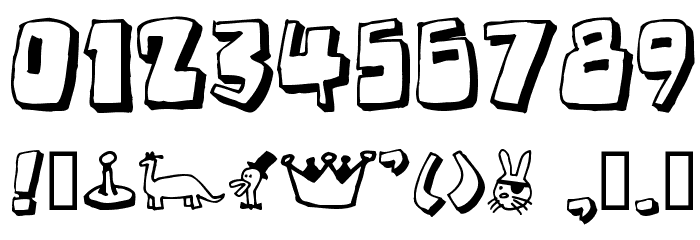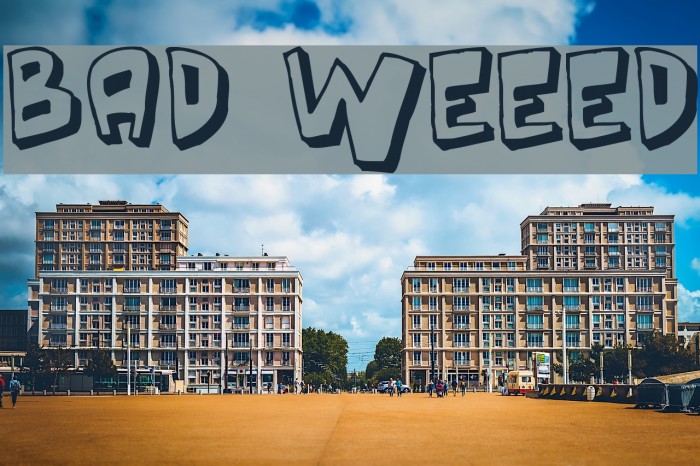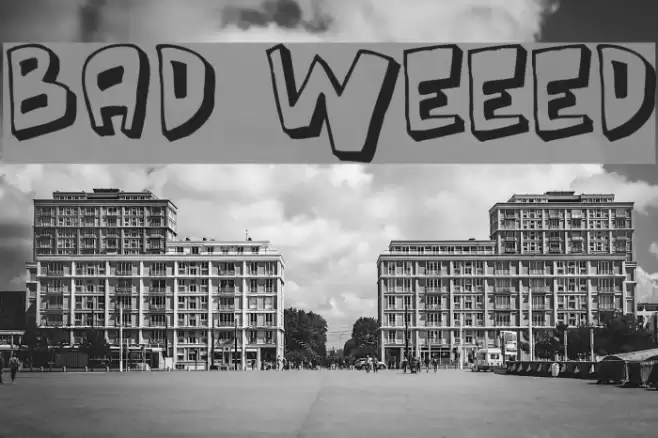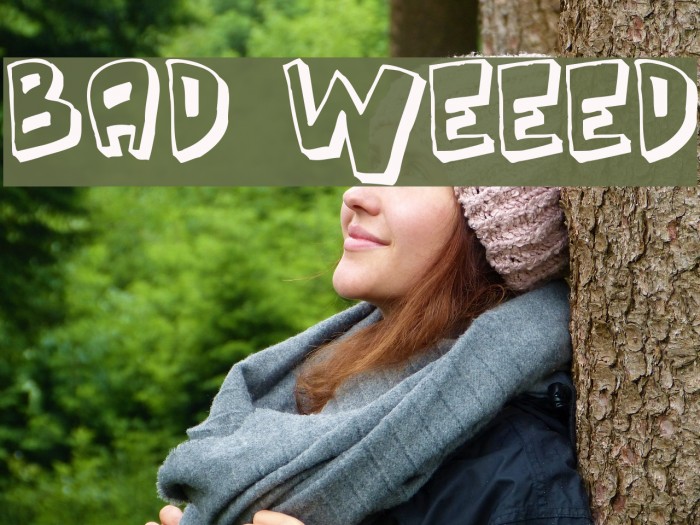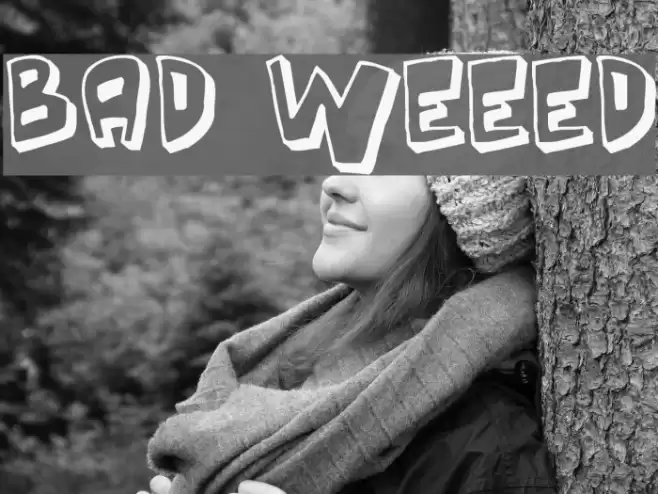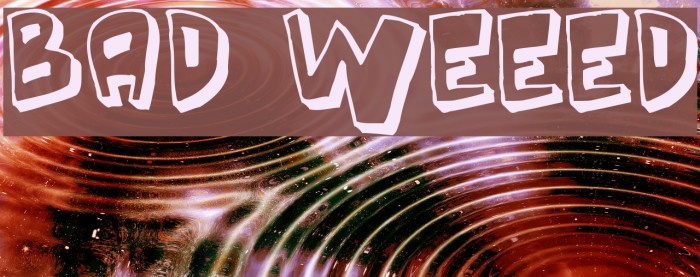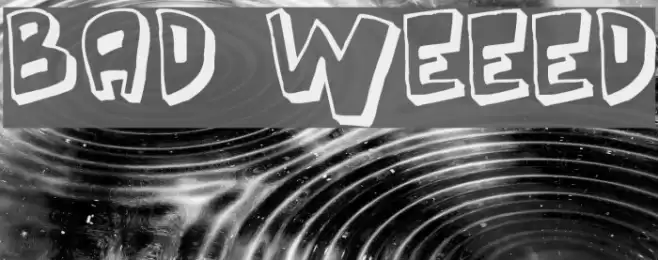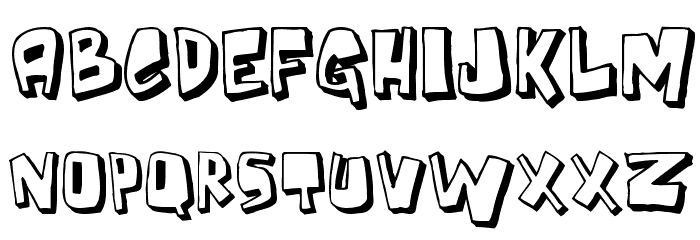
Bad Weekend Font
✎ Outline
| 名前 | Bad Weekend |
| カテゴリ | Outline |
| 全体的なスタイル | Playful, Cartoonish, Whimsical |
| おすすめプロジェクト | Ideal for children's books, comic strips, playful branding, and creative posters. |